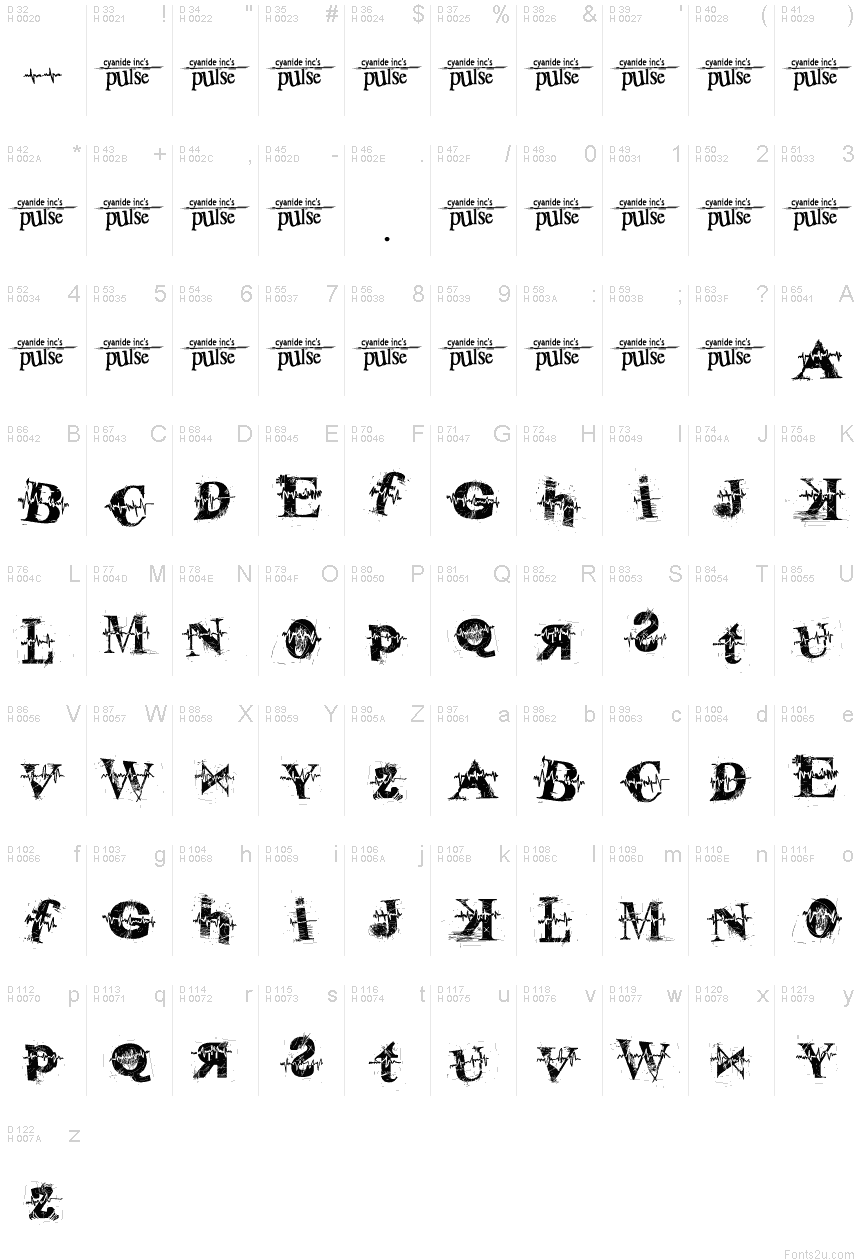
Pulse Sans to darmowy, distressedowy font typu display z głośnym, elektro-punkowym rytmem w dużych literach. Litery sprawiają wrażenie zniszczonych i wielokrotnie nadrukowanych, pełnych szorstkich pęknięć, zadrapań i postrzępionej linii tętna, która przecina słowo niczym szum z uszkodzonego monitora.
Świetnie pasuje do plakatów muzycznych, klubowych ulotek, okładek mixtape’ów, plansz tytułowych i grafiki streetwearowej, gdzie ten darmowy font nadaje krótkim liniom tekstu dynamizmu i surowości. Użyj go do nazw, haseł lub dużych inicjałów, gdy chcesz, by litery sprawiały wrażenie poszarpanych i pełnych energii, zamiast czystych czy ułożonych.